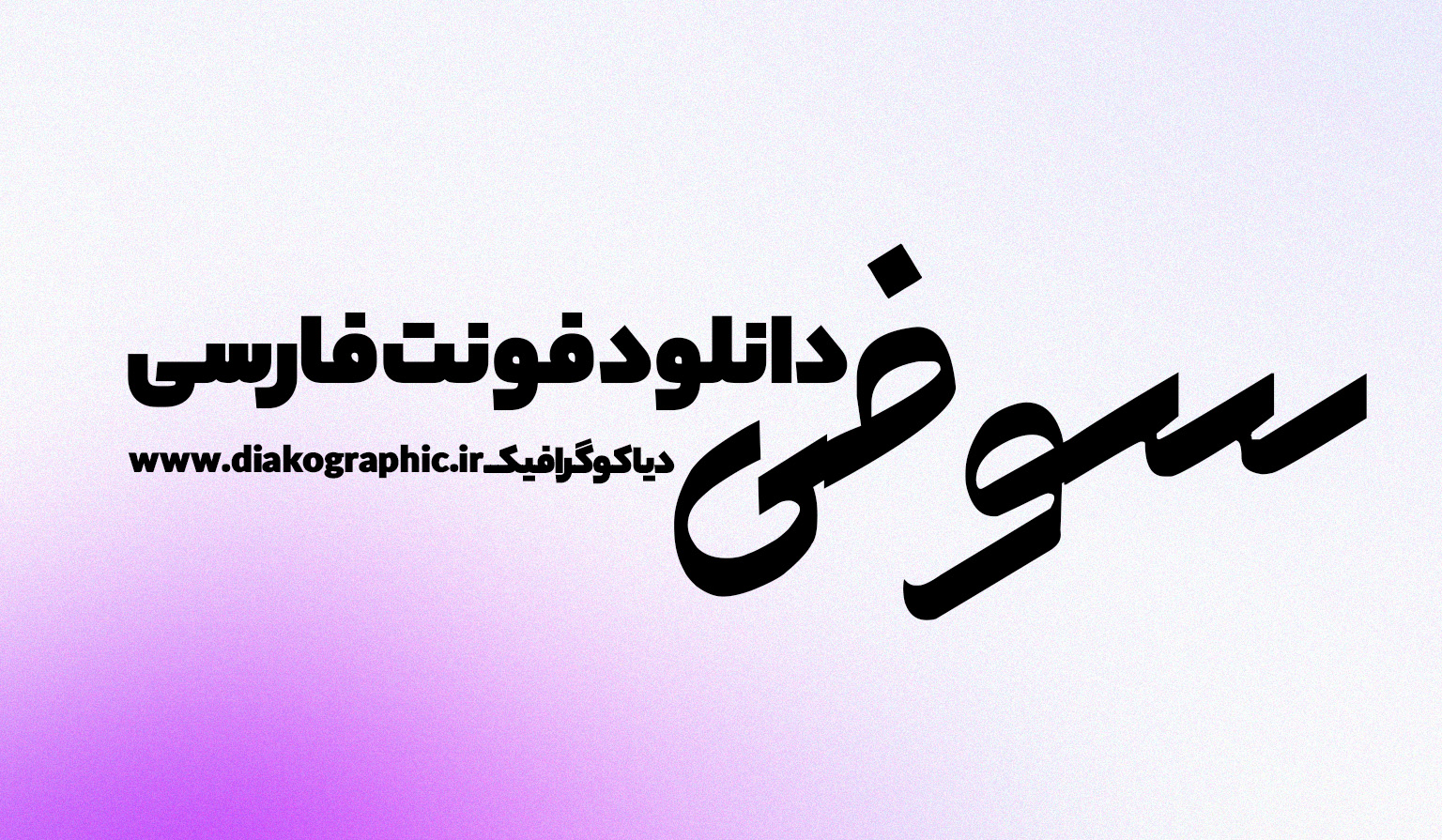
اگر به دنبال یک فونت فارسی خاص و زیبا برای طراحیهای گرافیکی خود هستید، بدون شک فونت سوفی یکی از بهترین انتخابها برای شما خواهد بود. این فونت با استایل دستنویس و جذاب خود، حس صمیمیت و خلاقیت را به پروژههای شما میبخشد. در این مقاله از دیاکوگرافیک، به بررسی کامل فونت سوفی، کاربردهای آن، مزایا و نحوه دانلود فونت سوفی میپردازیم.
فونت سوفی چیست؟
فونت سوفی یک فونت فارسی با طراحی دستنویس است که به دلیل فرم نرم، روان و دوستداشتنی حروف، بهسرعت جای خود را در بین طراحان گرافیک و علاقهمندان به تایپوگرافی باز کرده است. این فونت در دستهی فونتهای تزئینی و احساسی قرار میگیرد و مناسب استفاده در طرحهای دوستانه، شخصی و هنری است.
چرا باید فونت سوفی را در پروژههای خود به کار ببریم؟
- ظاهر دستنویس و صمیمی: فونت سوفی ظاهری شبیه به دستخط دارد و همین ویژگی باعث میشود در طراحیهای دوستانه و شخصی بسیار کاربردی باشد.
- خوانایی بالا: با وجود استایل دستنویس، فونت سوفی از وضوح و خوانایی مناسبی برخوردار است.
- پشتیبانی از زبان فارسی: این فونت کاملاً با زبان فارسی سازگار است و از حروف فارسی، اعداد و علائم نگارشی پشتیبانی میکند.
- ظاهر مدرن و مینیمال: این فونت با ترکیب عناصر کلاسیک و مدرن، انتخابی عالی برای طرحهای امروزی به شمار میرود.
کاربردهای فونت سوفی در طراحی
فونت سوفی با انعطافپذیری بالا، در انواع پروژههای گرافیکی قابل استفاده است:
- طراحی کارت دعوت و کارت تبریک
- پست و استوری شبکههای اجتماعی
- لوگوتایپهای شخصی و هنری
- جلد کتاب و مجله
- پوسترهای تبلیغاتی با لحن غیررسمی
- تایپوگرافیهای خلاقانه
چرا فونت سوفی اینقدر پرطرفدار شده است؟
یکی از دلایل محبوبیت بالای فونت سوفی، ترکیب موفق سنت و مدرنیته در طراحی آن است. حروف آن نهتنها حالتی نرم و دلنشین دارند، بلکه حس شخصیسازیشده را نیز به مخاطب منتقل میکنند. این ویژگیها باعث شده تا فونت سوفی در بین طراحان، بلاگرها و صاحبان برندهای کوچک بسیار محبوب شود.
چگونه این فونت را حرفهای به کار ببریم؟
- در کنار فونتهای ساده مانند ایرانسنس یا وزیر استفاده شود تا خوانایی حفظ شود.
- برای طراحی با لحن دوستانه، فونت سوفی را با رنگهای پاستلی ترکیب کنید.
- در سایزهای بزرگتر، زیبایی منحنیهای دستنویس آن بیشتر به چشم میآید.
- فونت سوفی برای متون طولانی مناسب نیست؛ بهتر است برای تیترها یا جملات کلیدی استفاده شود.
فونت سوفی برای چه کسانی مناسب است؟
چه یک طراح گرافیک حرفهای باشید، چه بلاگری که به زیبایی بصری اهمیت میدهد، و یا حتی یک معلم یا نویسنده که به دنبال خلق محتوای خاص هستید، فونت سوفی میتواند جلوهای منحصربهفرد به کار شما بدهد. این فونت، به دلیل استایل احساسی و انسانی خود، در برقراری ارتباط بصری بسیار مؤثر است.